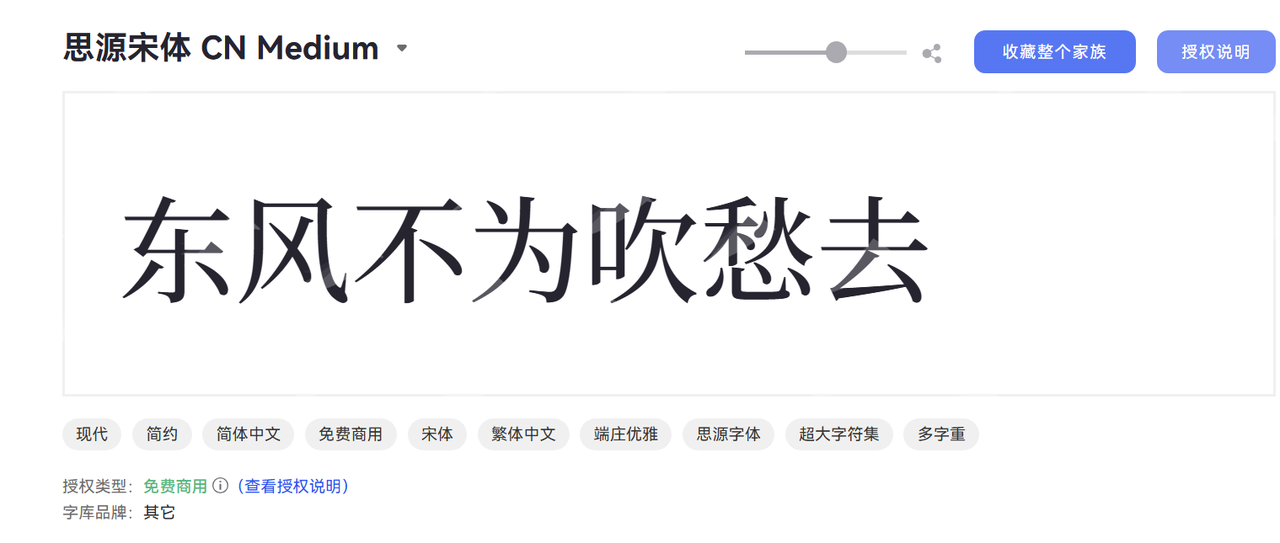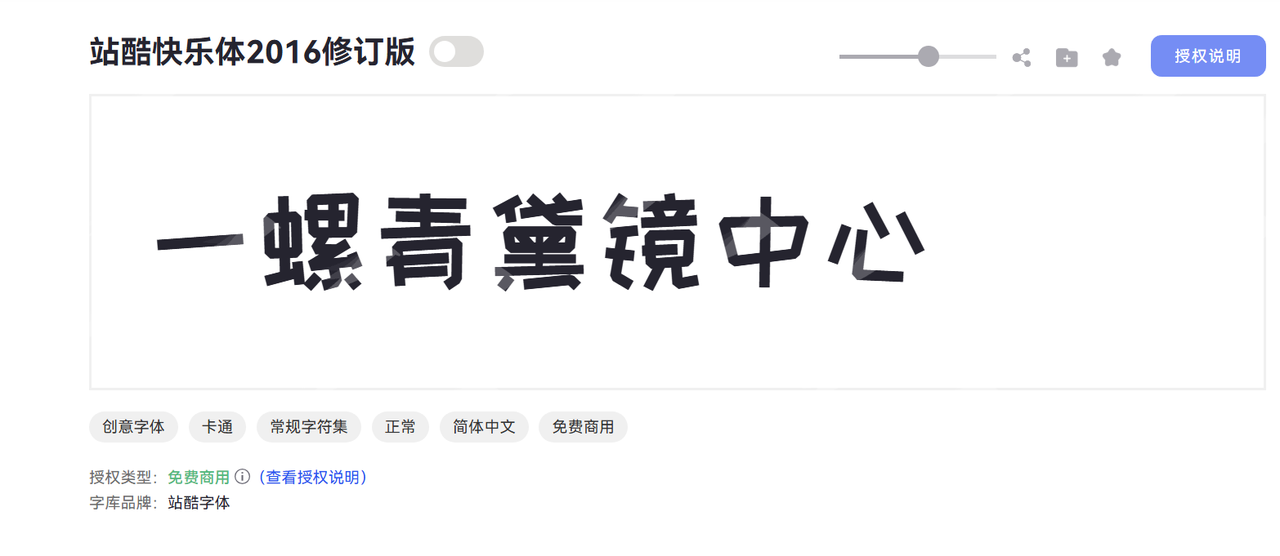
1.思源黑体
如果只能装一款中文字体,很多专业设计师会选思源黑体。这是谷歌与Adobe联合推出的开源字体,支持7种字重,不仅适合做标题,也能作为正文阅读字体,可以满足不同场景下的文字显示需求。 字由网上可以直接搜索并一键激活使用,日常设计、PPT、品牌物料全能覆盖。适用场景: 企业宣传、PPT、正文排版、UI界面
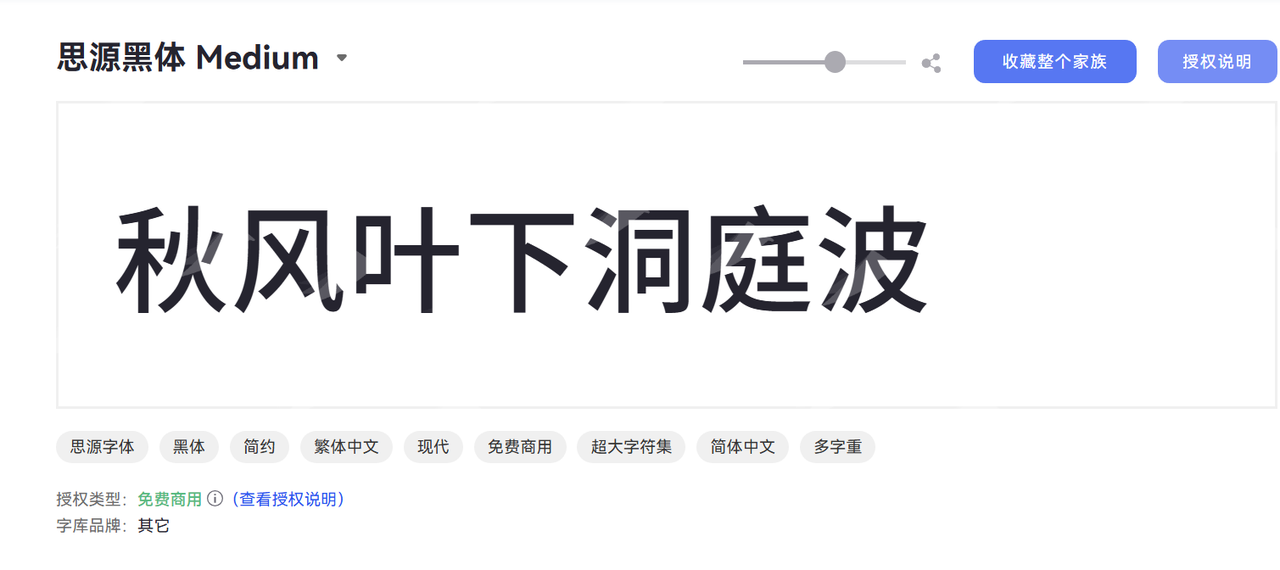
2.思源宋体
跟思源黑体同出一门,思源宋体的主旨本就是为了与思源黑体搭配使用,同样免费可商用。宋体给人"严肃、厚重"的第一印象,但思源宋体是个例外——字形雅致,气质偏文艺,用来做长图排版、杂志风海报、读书博主的封面都很适合。如果你厌倦了黑体一统天下的版面,思源宋体是个让整体调性立刻提升一个档次的选择。适用场景: 长文排版、公众号封面、文艺风海报、书籍封面
3.站酷快乐体 — 轻松活泼,带点烟火气
如果上面几款都偏"正经",那站酷快乐体就是反方向的代表。站酷快乐体活泼好看,曾被热门综艺节目使用,设计初衷是增加文字在屏幕上的辨识度,可免费商用,适合海报、名片、广告等场合。小红书博主、美食账号、生活类自媒体用这款字体特别合适。适用场景: 美食/生活类自媒体、节日海报、活动推广
4.阿里巴巴普惠体 — 互联网感十足,全场景通杀
阿里巴巴在2019年设计大会上发布了"阿里巴巴普惠体",该字体永久免费商用。 字形现代、干净,多字重覆盖了从超细到超粗的各种需求。如果你的项目追求的是那种"互联网大厂感"的简洁风格,这款字体基本上闭眼选就能用对。适用场景: App界面、互联网产品宣传、电商海报
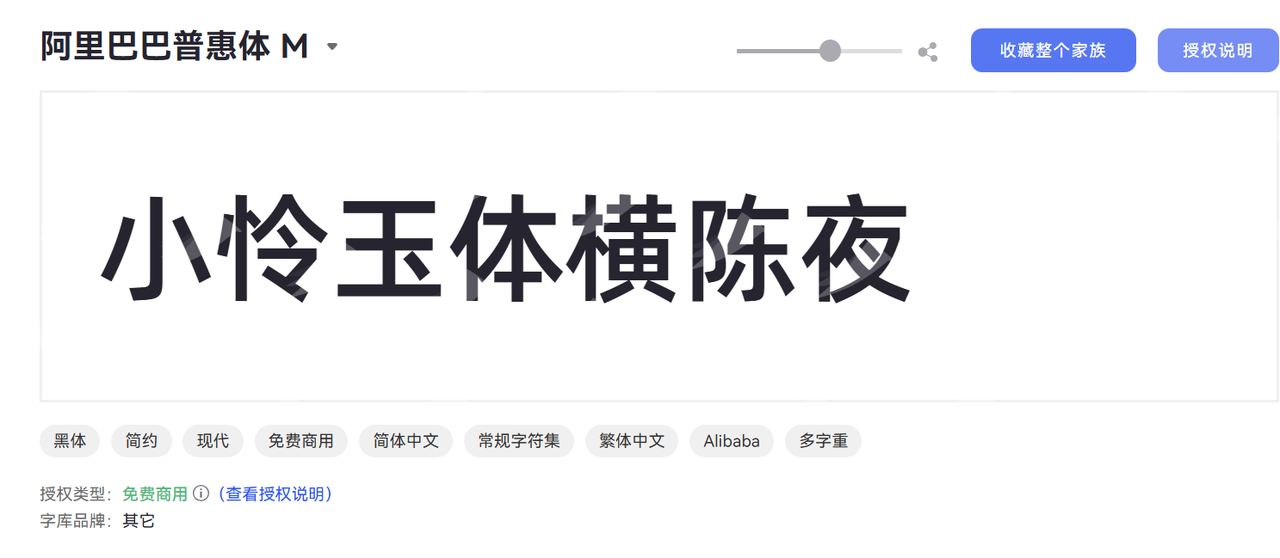
5.濑户字体 — 二次元风格的小众选手
濑户字体是一款偏可爱风格的字体,支持简体中文、繁体中文、日文,包含CJK常用汉字及假名。整体风格圆润可爱,带有明显的日系气质,用在动漫相关内容、萌系插画配文上效果极佳。不走主流路线的创作者可以考虑把它加进字体备用库,偶尔用在风格型内容上特别出彩。适用场景: 动漫/萌系内容、手账风排版、个性化创作